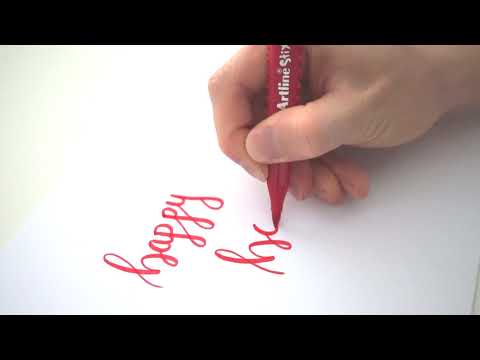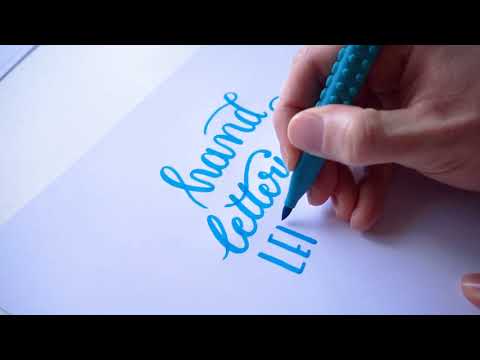
Vermutlich hast du schon bei einigen Handlettering Artists seltsame Brush Pens gesehen, die wie eine Kombination aus Stift und Legostein wirken. Was es damit auf sich hat und ob der Stift zum Lettern taugt, erfährst du hier.
Artline Stix Steckbrief
Die Stiftspitze
Bevor ich auf das Design der Stifte eingehe, möchte ich den wichtigsten Teil des Stiftes unter die Lupe nehmen.
Die Spitze der Brush-Pens ist relativ fest und etwas größer als beispielsweise die Spitze der Edding Brush Pens. Sie ist aber dennoch flexibel genug um als Pinsel-Spitze zu funktionieren.
Damit haben die Artiline Stix eine relativ große Bandbreite zwischen feiner Linie und dickem Abstrich. Besonders die feinen Linien erfordern allerdings einiges an Übung und Sicherheit mit dem Stift. Das liegt daran, dass du für eine feine Linie wirklich nur eine kleinen Bereich der Pinsel-Spitze zur Verfügung hast, während nahezu kein Druck auf der Spitze liegen darf.
Mit etwas Übung erzeugen die Artline Stix Brush Pens allerdings ein sehr schönes Schriftbild und erlauben auch etwas größere Schriftzüge als beispielsweise die Brush Pens von Edding.
Nochfolgend habe ich zwei Videos für dich, in denen ich die Artline Stix für zwei Schriftzüge verwende:
Was ich persönlich sehr mag, ist das beim Schreiben mit den Artiline Stix automatisch ein ganz dezenter Farbverlauf innerhalb einer Farbe entsteht. Der Anfang eines Abstrichs ist dabei meist ein ganz kleines bisschen dunkler, als das Ende. Das setzt natürlich voraus, dass du deine Abstriche nur einmal ziehen musst und sie nicht noch einmal nachmalst.
Das Legostein-Design
Vielleicht enttäuscht es dich, aber das Design ist zu 99% Spielerei. Man kann die Artline Stix damit zwar tatsächlich, wie Legosteine, aneinander befestigen aber wirklich nützlich ist das nicht. Die Stiftspitzen liegen dabei soweit auseinander, dass die Doppel-Linie, die du dann ziehst, viel zu breit ist.
Wenn man allerdings bedenkt, dass die Stifte eher für Kinder und nicht für uns Handletterer produziert wurden, ist es doch eine ganz lustige Idee. Die Tocher eines Freundes war jedenfalls fasziniert. 😉
Die Legostein-Haptik stört übrigens nicht beim Lettern, da der vordere Teil glatt ist und sich normal anfassen lässt.
Fazit
Die Artline Stix Brush Pens eignen sich sehr gut für einfache Handletterings und sind nach etwas Übung unkompliziert zu benutzen. Sie sind realtiv robust und vertragen auch mal einige Striche auf rauerem Papier. Im Paket sind viele, besondere Farben, die sonst nicht in jedem Stifte-Set vorhanden sind.